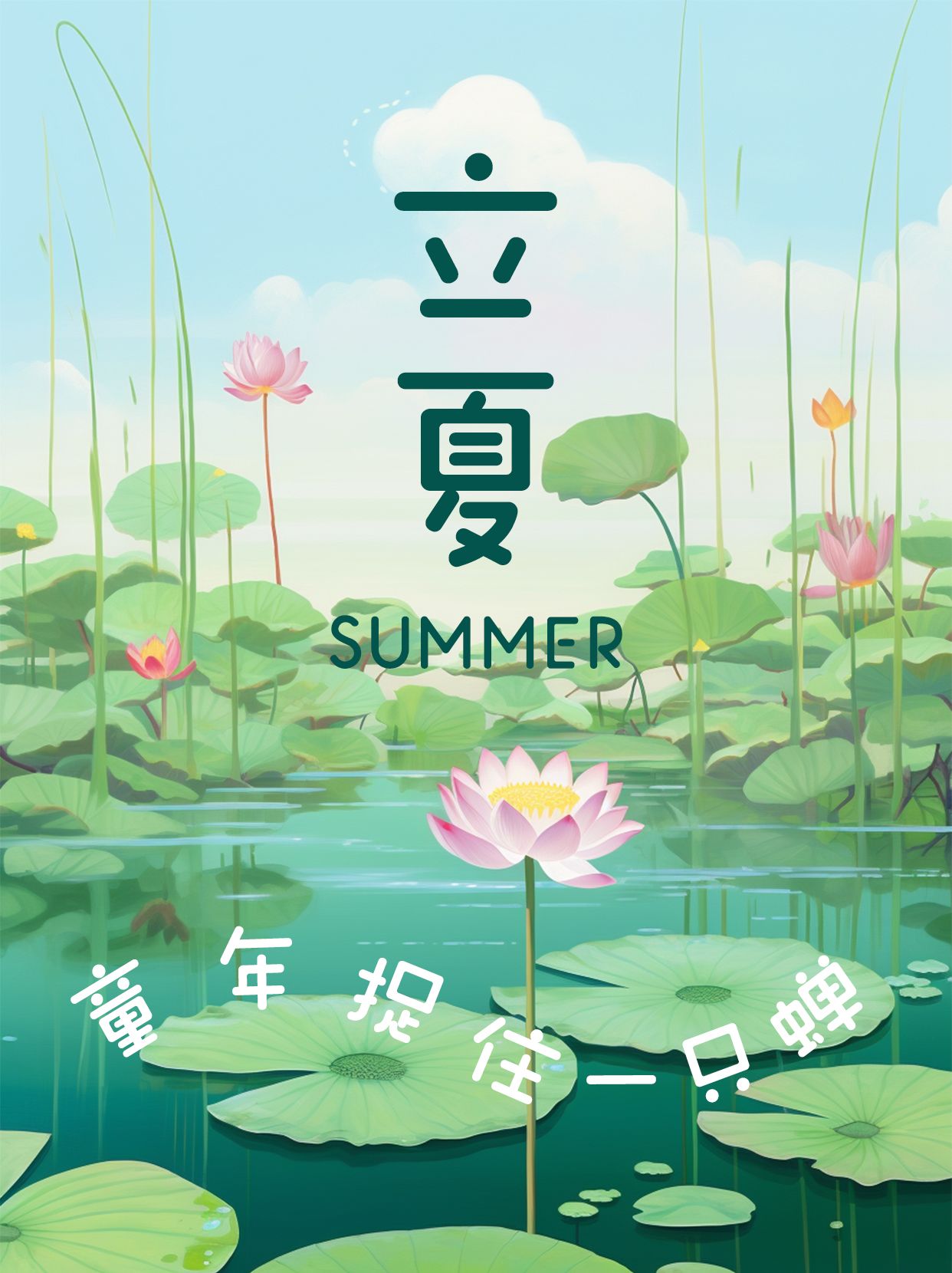
爆款电商行业用字字体推荐
在竞争激烈的电商行业中,字体不仅是信息的载体,更是品牌形象的重要组成部分。一款合适的字体能够瞬间提升产品的吸引力和品牌的辨识度。以下是几款专为爆款电商行业设计的字体推荐:
在电商行业,一款合适的字体能瞬间吸引顾客眼球。造字侠郝刚快乐简 微黑,以其独特的笔画设计与微黑风格,成为爆款电商用字的优选。这款字体融合了创意与快乐元素,字形流畅而富有动感,既展现了电商的活力与时尚,又不失稳重与可读性。无论是产品标题、促销信息还是品牌宣传,造字侠郝刚快乐简 微黑都能完美呈现,助力电商品牌脱颖而出。
在电商的广阔舞台上,一款强有力的字体是吸引流量的秘密武器。励字志向黑简 大粗,以其磅礴的气势和粗犷的线条,成为电商行业的爆款之选。这款字体不仅展现了产品的力量感与品质感,还巧妙融合了志向与激情,让每一个文字都充满力量,直击消费者内心。无论是促销标语还是品牌标识,励字志向黑简 大粗都能让您的电商店铺在众多竞争者中脱颖而出,引领潮流。
在追求个性与温馨的电商领域,励字小桃气简繁 常规圆以其独特的圆融美感,成为爆款用字新选择。这款字体融合了简约与可爱元素,字形圆润而不失精致,透露出一种温馨可人的气息,完美契合电商行业对于用户体验的极致追求。无论是商品描述、活动海报还是品牌故事,励字小桃气简繁 常规圆都能为您的电商店铺增添一抹温柔与亲切,吸引更多顾客的目光与喜爱。
在电商的浩瀚宇宙中,励字造梦简 大粗以其粗犷而不失细腻的笔触,成为引领潮流的爆款字体。这款字体蕴含着造梦者的激情与决心,大粗的线条如同坚实的基石,支撑起每一个电商品牌的梦想。它不仅赋予了文字强大的视觉冲击力,更激发了消费者的购买欲望。选择励字造梦简 大粗,让您的电商店铺在众多竞争者中脱颖而出,共同编织属于品牌的辉煌篇章。
以上几款字体各具特色,能够满足不同电商品牌的设计需求。在选择字体时,建议根据品牌形象、目标受众和传达的信息综合考虑,以达到最佳的视觉效果和用户体验。